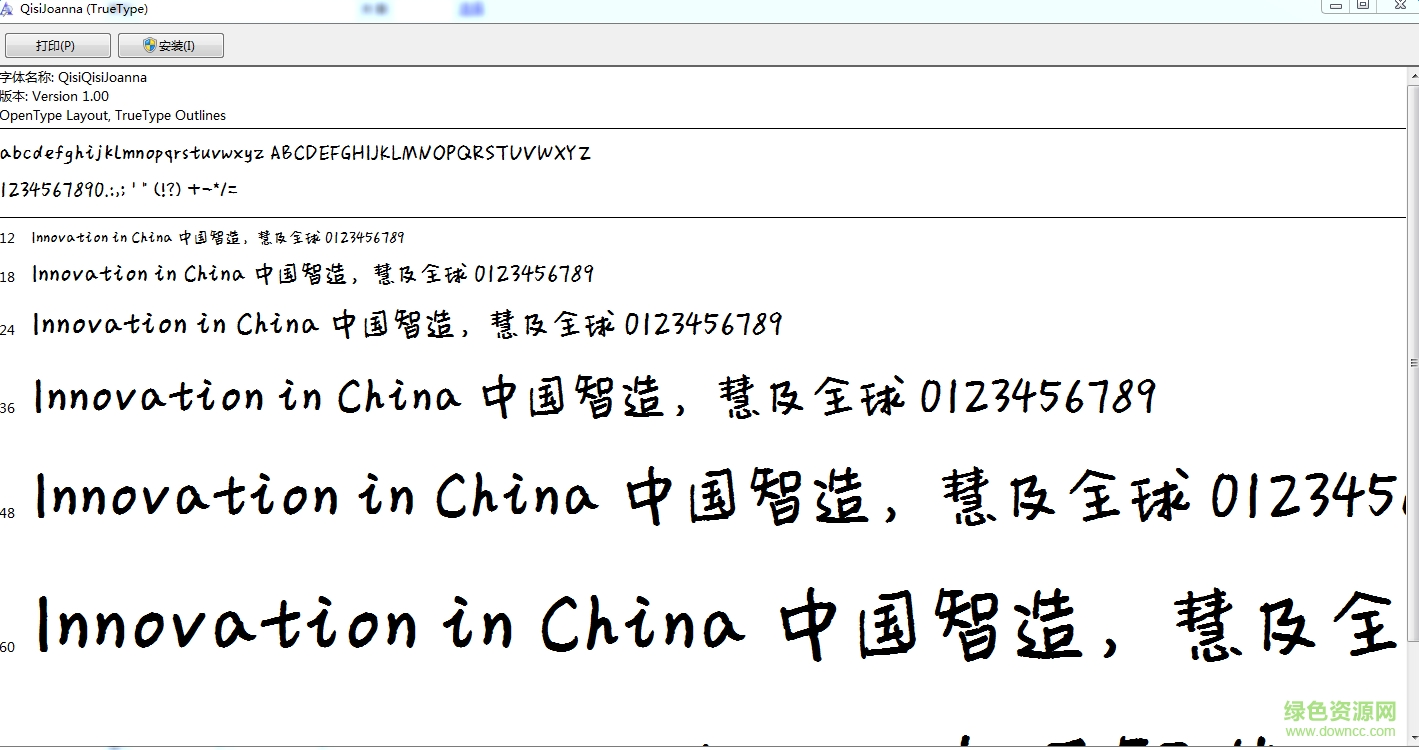
安娜娜字體ttf版是一款電腦版的奇思字體,該字體筆形柔和,線條舒緩,玲瓏秀美,帶有濃濃的手寫體風(fēng)格,應(yīng)用于各種手工設(shè)計(jì)或廣告設(shè)計(jì)都可以!
字體小巧,筆畫生動(dòng),造型優(yōu)美,于活潑稚氣中顯現(xiàn)出設(shè)計(jì)構(gòu)思的精巧,易讀性和欣賞性兼?zhèn)?!適合兒童讀物、報(bào)刊雜志標(biāo)題、廣告等領(lǐng)域!